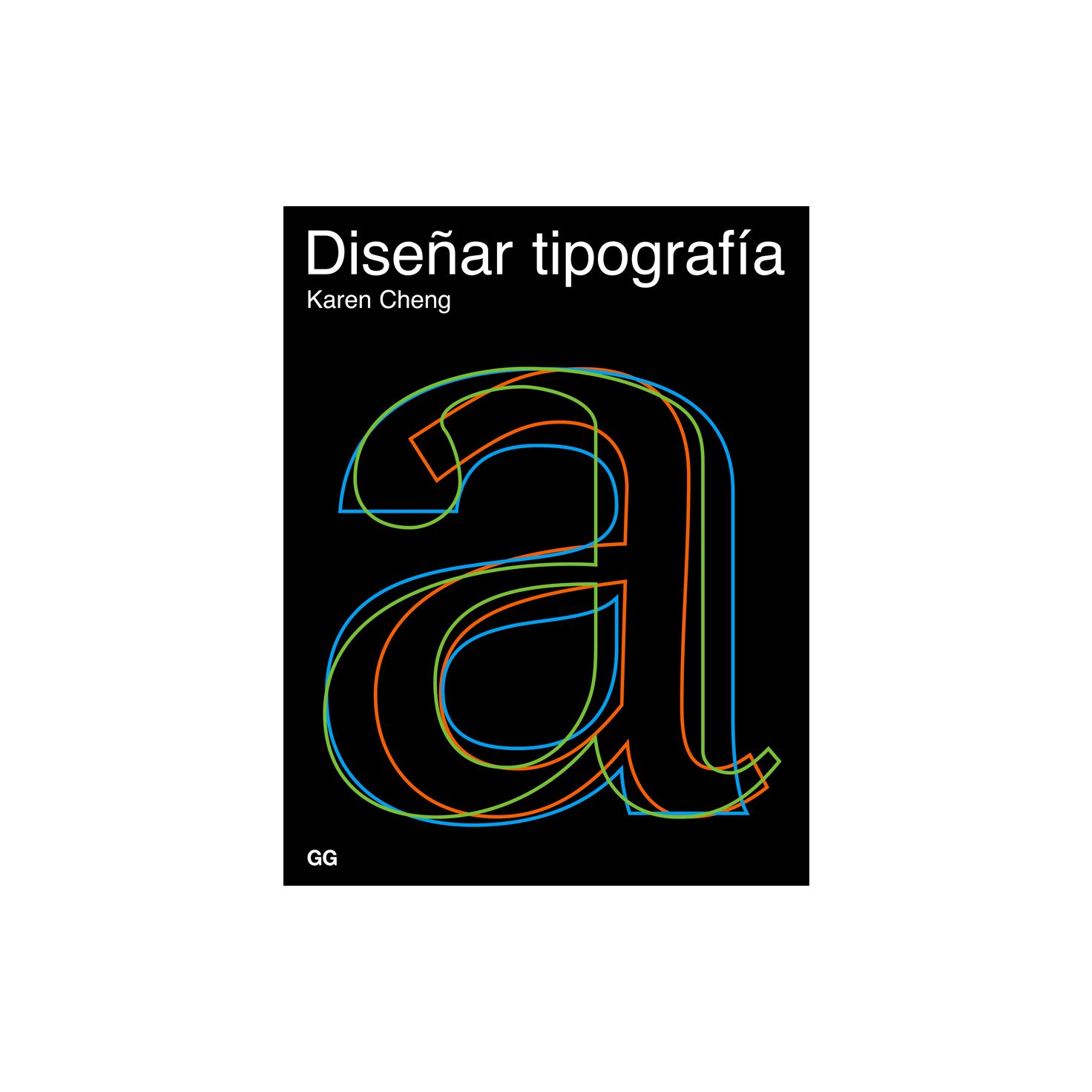
Diseñar tipografía
Diseñar tipografía es un manual completo y detallado especialmente destinado a tipógrafos, diseñadores gráficos y estudiantes. Ampliamente ilustrado, con ejemplos y diagramas que muestran los principios visuales y la construcción de las letras, este libro abarca desde temas como la estructura, la compensación óptica y la legibilidad hasta las relaciones entre las letras y las formas de cada fuente tipográfica. Además de estudiar un amplio abanico de tipografías clásicas y contemporáneas, el libro presenta un gran número de trabajos de estudiantes, bocetos y diseños definitivos. Ante la creciente demanda de tipografías originales y creativas, Diseñar tipografía es un libro de referencia indiscutible tanto para los profesionales con experiencia como para los diseñadores que están empezando.
Índice de contenidos: Introducción El proceso de diseño Variables en el diseño de tipos Partes de una letra Clasificación de los tipos Las mayúsculas con remates O E C G D B P y R J Q S I, H, T, F y L V y A U X W Y M N K Z Las minúsculas con remates o y l d, q, b y p e y c n, h, m y u r a s g i y j f y t v, w e y k x y z Las mayúsculas sin remates O y E I, H, T, L y F S, C y G U y J D, B, R y P Q V, A y W K, X e Y M, N y Z Las minúsculas sin remates o y l d, b, p y q s, c y e a y g n, m, h, u y r i, j, f y t v, w y y k, x y z Los números 0 y 1 2 4 7 3 y 5 6 y 9 8 La puntuación El punto, la coma, los dos puntos y el punto y coma Las comillas El signo de interrogación y el signo de exclamación Signos diacríticos El acento agudo y el acento grave El acento circunflejo El umlaut y la diéresis La tilde de la ñ La cedilla La eszett o ß alemana El espaciado Los entornos de las letras Comprobar el espaciado El espacio entre palabras, números y puntuación El kerning Bibliografía Índice Agradecimientos |
Texto de la introducción: ‘Introducción El lenguaje es la característica humana más significativa. Mediante un sistema complejo de signos, sonidos y símbolos somos capaces de comunicar las ideas y los mensajes de nuestra sociedad, que evoluciona de manera incesante y global -a su vez, dichas ideas y mensajes son una información que tiene el poder de moldear y cambiar la propia civilización-. La tipografía es la manifestación visual del lenguaje. Su papel es decisivo a la hora de convertir los caracteres individuales en palabras y las palabras en mensajes. En el terreno de la música, la calidad de un solo cantante puede hacer que una composición suene de manera completamente distinta. En el campo de la comunicación, la tipografía es el equivalente visual de una voz: el enlace tangible entre el escritor y el lector. Por supuesto, la tipografía no solamente hace que los mensajes sean legibles. La forma misma de los tipos matiza, incluso altera, el propósito inicial de un mensaje. Los caracteres tipográficos pueden estar cargados de poder simbólico. Algunos tipos representan comportamientos radicales (las fuentes góticas, por ejemplo, se asocian a las bandas callejeras), mientras que otros tipos representan lujo o jerarquía social (determinadas fuentes caligráficas se asocian a invitaciones formales o a anagramas regios). Además, la tipografía puede expresar emoción y personalidad. Los sentimientos negativos se pueden expresar con pesos gruesos y formas afiladas, mientras que los pensamientos amables se pueden evocar mediante caracteres elegantes y delicados. Incluso las fuentes que, debido a su amplio uso, se consideran “invisibles” -como la Univers, utilizada en este texto- tienen una personalidad distinta, aunque en este caso sus características sean la neutralidad y la racionalidad. A lo largo del siglo pasado se ha dado un crecimiento espectacular del número de tipos disponibles para los diseñadores y el público en general. Gran parte de este crecimiento es resultado de la implantación de las nuevas tecnologías. Así, se han diseñado fuentes para pantallas de baja resolución, para navegar en Internet, para el reconocimiento óptico de caracteres, o para interfaces de PDA (Personal Digital Assistant). Otros tipos se han diseñado teniendo en cuenta, principalmente, criterios funcionales: tipos optimizados para la legibilidad a larga distancia, en la señalización de autopistas o para la impresión en papel de poca calidad, como la de periódicos y guías de teléfono. Otras tipografías se han diseñado para públicos específicos como, por ejemplo, niños que empiezan a leer, disléxicos y personas con problemas de vista. Sorprendentemente, a pesar del creciente interés y de la necesidad de nuevas tipografías, existen muy pocos libros que expliquen los aspectos generales relacionados con el diseño de fuentes -como el equilibrio óptico y visual de las letras- o las cuestiones técnicas de la producción digital de tipos. Este libro intenta paliar el vacío existente en este terreno. Por ello, explica detalladamente el diseño de caracteres encaminado a construir un alfabeto unificado y, al mismo tiempo, de formas variadas; asimismo, se ocupa del proceso de espaciado necesario para acabar correctamente una fuente. Los siguientes capítulos dividen el alfabeto en varias partes: las letras mayúsculas, las letras minúsculas, los números, los signos de puntuación y los signos diacríticos y otros caracteres especiales. Los tipos se organizan en dos grandes categorías: con remates y sin remates o sanserif. A su vez, las fuentes con remates se clasifican de acuerdo con las cinco categorías principales establecidas por Maximilien Vox: venecianas, garaldas, de transición, didonas y mecanas o egipcias. Dentro de las fuentes sanserif se han incluido los siguientes grupos: grotescas, neogrotescas, sanserif geométricas y sanserif humanistas. Los ejemplos tipográficos seleccionados muestran cierta preponderancia de los tipos clásicos de texto frente a las fuentes más actuales para titulares. Esto se ha hecho así para ofrecer la posibilidad del análisis más exhaustivo en cuanto a soluciones de diseño. En una fuente para titulares o decorativa existen pocas preocupaciones respecto al color y la estructura, ya que las fuentes decorativas se usan en cuerpos muy grandes y con mucha menor frecuencia. Este libro se ha planteado como un manual de referencia tanto para el diseñador principiante como para el tipófilo con experiencia. Por este motivo, se incluyen ejemplos de bocetos del diseño de distintas tipografías, junto con gráficos que muestran principios visuales e ilustraciones de la anatomía de las letras. Así, compartiendo no sólo el análisis sino también la inspiración, este libro espera aportar profundidad y orden al proceso y al arte que es el diseño de tipos.’ Copyright del texto: Karen Cheng Copyright de la edición: Editorial Gustavo Gili SL |